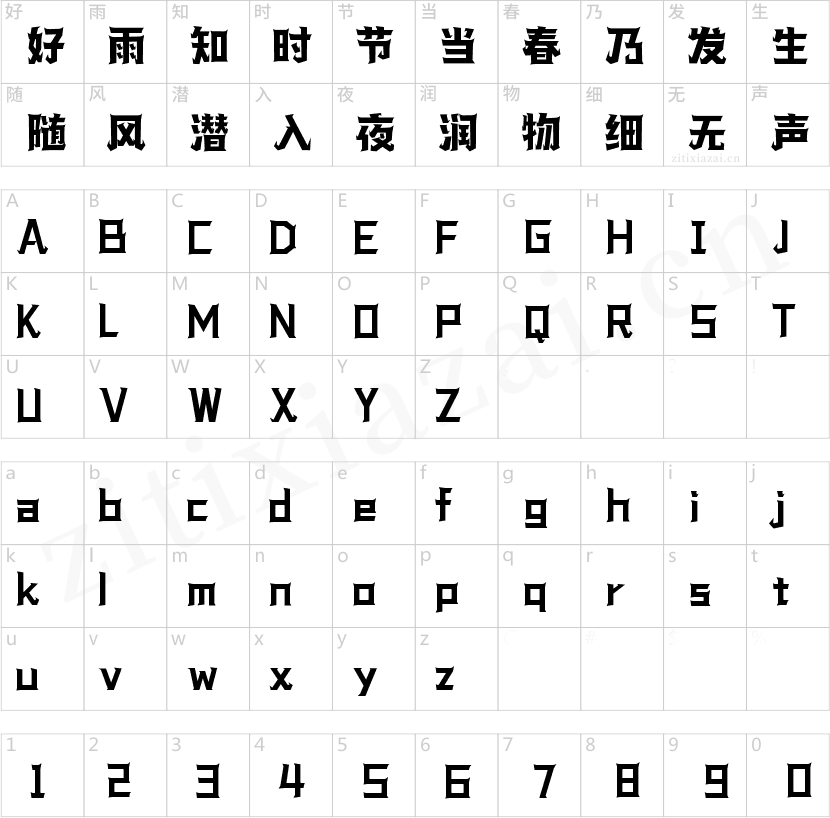
壹心魔法体
壹心魔法体,这款字体结构工整、笔画清晰,兼顾美观与易读性,适用于标题、正文、海报、包装、LOGO 等多种场景。字形优雅稳定,风格百搭耐看,适配日常排版与创意设计,让文字呈现更舒适、更具质感。壹心魔法体一笔一画,皆是细节,以均衡的比例、流畅的线条打造舒适视觉体验,字形端正大气,风格简约现代。无论是商业设计、品牌宣传还是日常排版,都能轻松驾驭,让文字更有格调与力量。壹心魔法体字体下载。